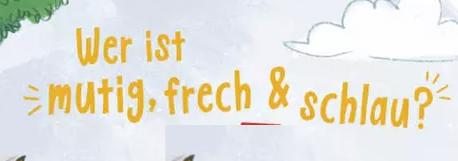
Suche "kindliche" Handschrift verwendet von Sonnentor
kennt jemand diese Schrift? Hab den Screenshot von www.sonnentor.com.
Bin mir nicht sicher ob die Schrift vielleicht auch extra entwickelt wurde?!